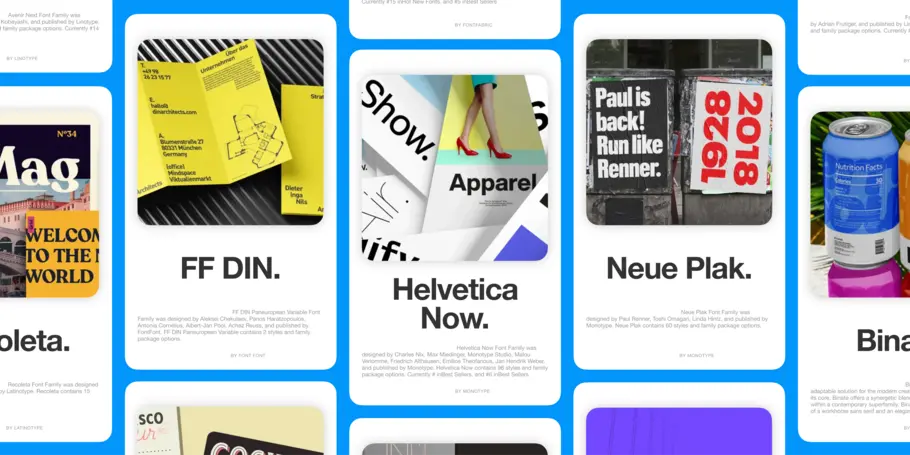
Designers : bien choisir votre fournisseur de polices
“ Découvrez les principales fonctionnalités qui vous aideront à choisir une police de caractères. ”
Choisir une police en ligne pour représenter votre marque, cela peut sembler parfois décourageant. Cela l’est d’autant plus lorsque vous essayez de trouver un équilibre entre les besoins de vos clients et ceux de vos parties prenantes. Après tout, la police de caractères que vous choisissez est l’une des premières choses que les gens voient lorsqu’ils regardent votre marque.
La bonne police peut donner le ton et, si elle est bien choisie, elle peut même incarner les valeurs fondamentales de votre marque et l’émotion que vous souhaitez transmettre à vos clients lorsqu’ils pensent à vous.
À moins que vous n’ayez une fonderie spécifique à l’esprit pour votre projet, vous commencerez probablement à chercher votre typographie dans une bibliothèque de polices. Pourquoi ? Eh bien, parce que les bibliothèques de polices proposent généralement des milliers de polices et elles jouent différents rôles : marketplace pour les polices payantes, dépôt de polices gratuites ou service d’abonnement.
La manière dont vous commencez votre recherche a une réelle importance. À vrai dire, la réussite de votre projet peut en grande partie en dépendre. Voici ce qu’il faut regarder lorsque vous choisissez un fournisseur de polices de caractères.
Une bibliothèque de polices bien conçue propose…
Que votre projet soit à destination d’un ordinateur, d’un téléphone portable ou d’un document imprimé, lorsque vous choisissez un fournisseur de polices de caractères, il est essentiel d’opter pour celui qui répond à vos besoins.
Découvrez les principales fonctionnalités qui vous aideront à la fois à déterminer le fournisseur adapté à vos besoins et à choisir une police de caractères faite pour votre projet.
La compatibilité.
En raison de la nature transversale inhérente à la stratégie de marque, il est important que vos polices soient compatibles avec plusieurs appareils. Si vous créez un texte pour votre site Web, vous devez vous assurer que la police fonctionne également sur un appareil mobile, dont l’écran et la résolution sont plus petits.
Dans le contexte actuel de la mondialisation des marchés, vous devez également choisir une police qui fonctionne dans toutes les langues. La police choisie doit prendre en charge, sans aucune erreur, les caractères requis pour les différentes langues. Si une police n’est pas conçue pour être totalement compatible avec plusieurs langues, vous risquez de constater un défaut ou un glyphe incorrect dans le texte. Perdre des clients potentiels à cause d’une incompatibilité de police n’est pas une chose souhaitable. Il est donc essentiel de choisir une bibliothèque de polices qui vous assure que vos polices fonctionnent pour tous les publics.
La partageabilité.
Un autre aspect important de votre police, c’est qu’elle puisse être partagée. Souhaitez-vous que toute votre équipe ait accès à la police ? Si c’est le cas, préférez-vous télécharger les polices sur chaque appareil ou utiliser une plateforme de gestion des polices basée sur le cloud ? Une fois que vous avez déterminé le niveau de partage dont votre équipe a besoin, vous pouvez choisir une bibliothèque de polices offrant les options de téléchargement correspondantes. Si votre bibliothèque de polices ne permet qu’à un seul utilisateur de visualiser ou de télécharger des polices, cela peut avoir un impact considérable sur les ressources et la productivité.
La haute qualité.
À première vue, cela peut sembler évident. Mais le fait est que certaines polices sont de meilleure qualité que d’autres, notamment en ce qui concerne la lisibilité à l’écran. Souvenez-vous de la dernière fois que vous avez lu du texte sur une application mobile. Est-ce qu’il était facile à lire ? Auriez-vous aimé que la police soit plus grasse ? Y avait-il suffisamment d’espace entre chaque lettre ? Tous ces détails sont essentiels pour que votre client ait envie de continuer à lire. Si votre police n’est pas lisible, votre client risque d’abandonner sa lecture et de quitter votre site Web ou votre application, sans même avoir été plus loin que la page d’accueil.
Toutes les bibliothèques de polices disposent d’une certaine gamme de polices. Mais une bibliothèque de polices bien conçue propose des polices avec plusieurs graisses et options de style pour assurer la lisibilité des polices sur tous les appareils. Soyez attentif au rendu du texte et aux caractéristiques typographiques, qui peuvent dysfonctionner avec certaines tailles de support. L’élément le plus important pour l’ergonomie d’une police est la précision de sa conception. Il arrive qu’une police ne se traduise pas bien d’un support à l’autre – par exemple d’un écran mobile à un panneau d’affichage immense. Lorsque cela se produit, c’est souvent lié à des problèmes de ​​dimensionnement optique (qui n’est qu’un exemple de police de caractères de meilleure qualité).
Si la forme et l’espacement des caractères d’une police affectent la lisibilité dans certaines tailles, le client est moins à même de comprendre votre message. Vous devez donc vous assurer que vos polices fonctionnent correctement d’un point de vue technique sur votre site. Une bibliothèque de polices de qualité propose des polices conçues avec toute une série de caractéristiques qui garantissent un rendu toujours soigné de votre typographie.
La recherche simplifiée.
Il est essentiel que vous puissiez trouver la police qui vous convient. Plutôt que de passer des heures à chercher sur internet la police faite pour votre projet, les bibliothèques de polices bien conçues sont dotées d’une fonctionnalité de recherche intégrée. Cela vous permet de filtrer vos résultats de recherche pour trouver une police ayant les qualités typographiques et répondant aux mots-clés intuitifs que vous recherchez.